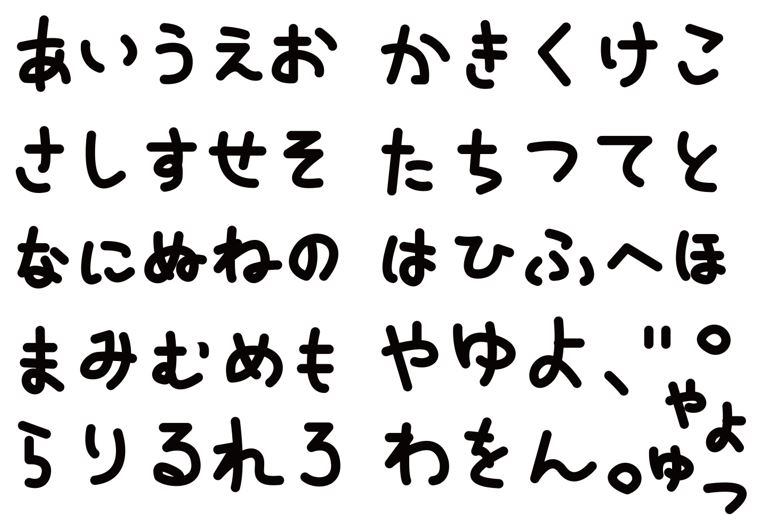
Phông chữ Nhật Bản là gì và sức hút của kiểu chữ phong cách này?
Font chữ Nhật Bản là hệ thống các phông chữ mô phỏng các nét vẽ thư pháp hoặc cấu trúc ký tự đặc trưng của xứ sở hoa anh đào. Đặc trưng của font Nhật Bản là sự kết hợp giữa những đường nét mạnh mẽ, dứt khoát của kiếm đạo và sự mềm mại, uyển chuyển của nghệ thuật trà đạo. Trong ngôn ngữ đồ họa, font chữ kiểu Nhật Bản mang lại cảm giác bền bỉ, tối giản và vô cùng tinh tế, rất phù hợp với các dự án quảng bá văn hóa và dịch vụ ẩm thực Á Đông.
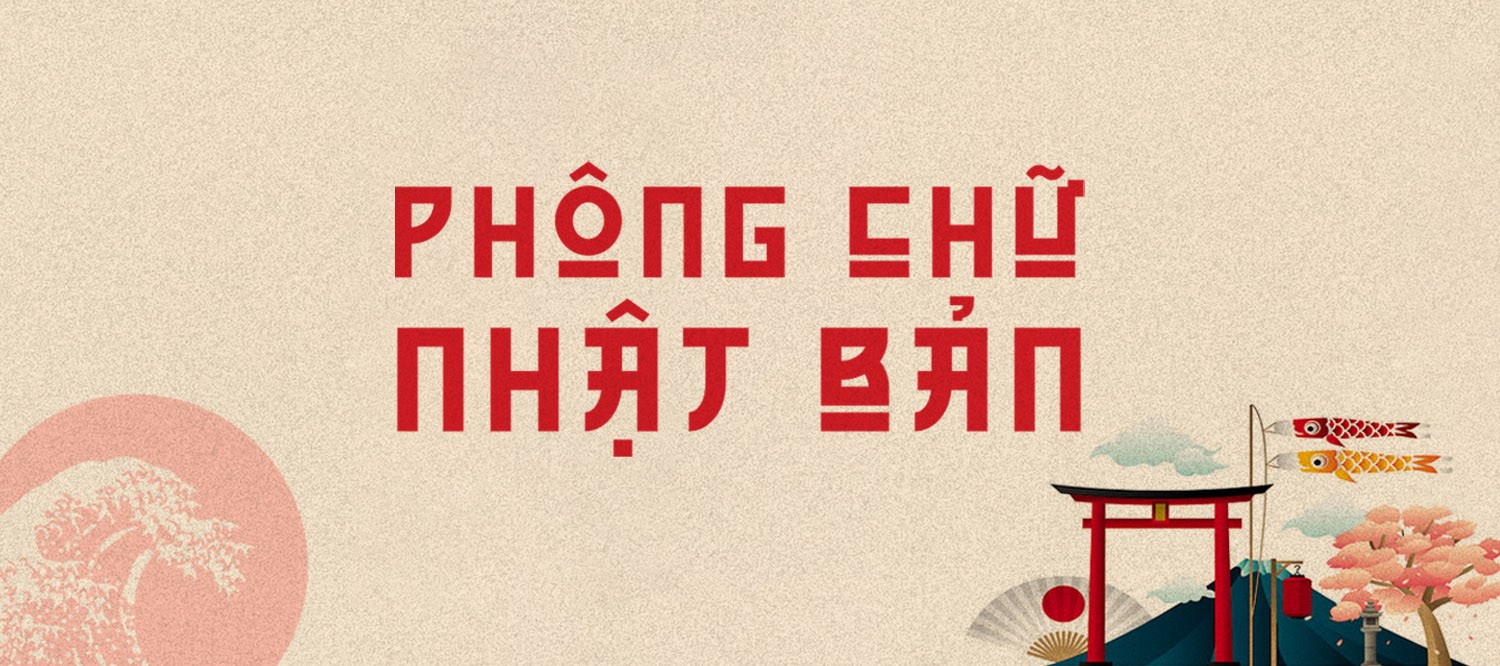
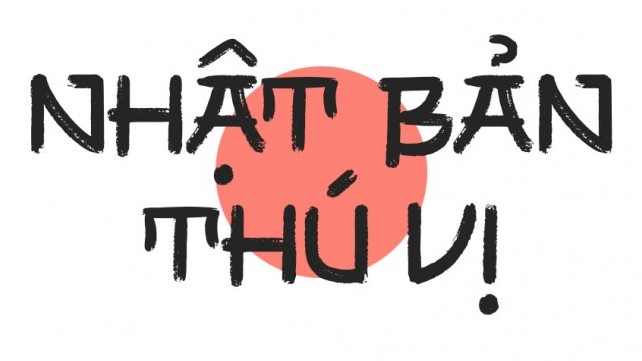
05 Ứng dụng phổ biến của font chữ phong cách Nhật Bản trong sản xuất
Vẻ đẹp mộc mạc và đặc trưng văn hóa của mẫu chữ này nâng tầm giá trị cho nhiều ấn phẩm truyền thông của đơn vị:
- Thiết kế bao bì nông sản và thực phẩm sạch: Sử dụng font chữ Nhật Bản để in trên các dòng túi giấy Kraft đựng trà, gạo hoặc thực phẩm sấy. Những nét chữ tự nhiên tạo cảm giác sản phẩm có nguồn gốc từ thiên nhiên, an toàn và dễ dàng tạo thiện cảm với người tiêu dùng.
- Sản xuất bộ ấn phẩm tri ân khách hàng: Font chữ Nhật Bản đẹp là lựa chọn phù hợp cho các dòng thông điệp vinh danh trên thẻ thành viên hoặc thiệp mời sự kiện. Sự kết hợp giữa nét chữ phá cách và kỹ thuật in hiện đại giúp hiện vật trở nên sang trọng.
- Gia công in UV trên các sản phẩm văn phòng: Logo dùng font Nhật Bản được in trên bình giữ nhiệt kim loại hoặc sổ tay da. Độ sắc sảo của tệp vector giúp các đường cong uốn lượn hiển thị rõ ràng trên các bề mặt sẫm màu, tạo vẻ ngoài bền bỉ.
- Trang trí không gian nhà hàng và Spa: Sử dụng font chữ Nhật Bản Việt hóa cho các câu slogan trên bạt backdrop hoặc chữ nổi mica. Đường nét uyển chuyển của chữ giúp không gian làm việc toát lên sự thư giãn và chuyên nghiệp.
- In nung gốm sứ bộ lưu niệm: Hình ảnh chữ nghệ thuật dùng phông Nhật Bản in nung trên men sứ trắng mang lại vẻ đẹp nhã nhặn, cổ kính cho các bộ ấm chén, là hiện vật trưng bày tinh tế cho các buổi lễ ký kết.
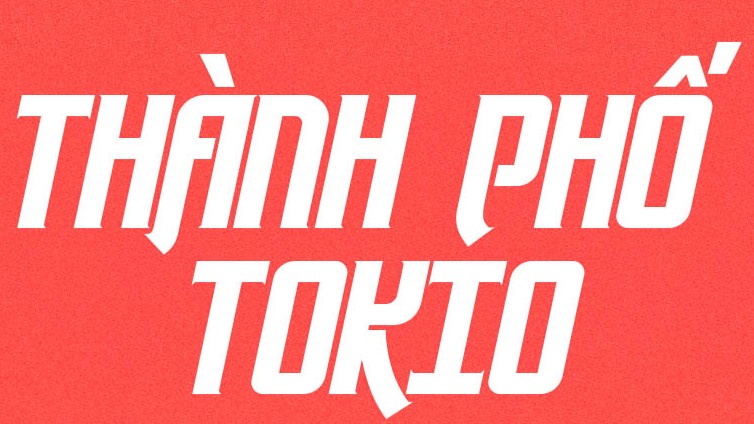
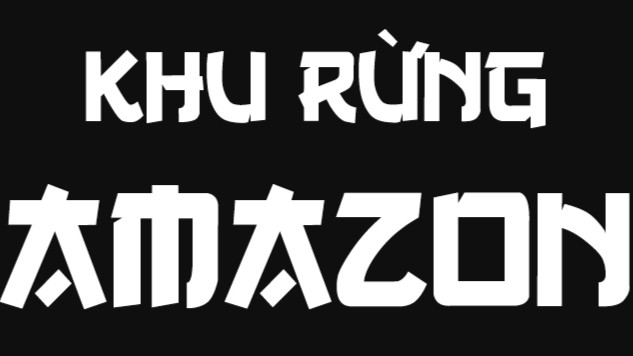
04 Lưu ý kỹ thuật khi sử dụng phông chữ Nhật Bản in ấn
Để hệ thống ký tự font chữ Nhật Bản full hiển thị sống động và bền màu trên các thành phẩm thực tế như túi giấy cao cấp hay hiện vật tri ân đối tác, designer cần chú trọng:
- Kiểm soát độ dày nét theo vật liệu: Font chữ Nhật Bản thường có nhiều nét móc và vòng xoáy nhỏ giả lập vết cọ. Khi in trên túi giấy Kraft có độ thấm mực cao, bạn nên chọn biến thể có nét dày để tránh tình trạng mực loang làm chữ bị dính vào nhau gây mất dáng chữ.
- Tối ưu đường Path cho gia công bế nổi: Bước này quan trọng khi sản xuất nắp hộp cứng dập nổi logo doanh nghiệp. Kỹ thuật viên cần làm mượt từng điểm neo tròn trong file vector giúp khuôn bế thực hiện chính xác, tạo hiệu ứng nổi khối rạng rỡ cho các chi tiết uốn lượn mà không làm rách giấy mỹ thuật.
- Thiết lập hệ màu CMYK cho dải màu rực rỡ: Chữ kiểu Nhật thường đi cùng các tông màu đỏ chu sa hoặc cam đất. Designer cần hiệu chỉnh hệ màu CMYK chuẩn và yêu cầu xưởng in mẫu thử để đảm bảo màu chữ sau in không bị ám xám hay mất sắc độ so với bản vẽ gốc.
- Bảo toàn tính chính xác của dấu thanh: Font Nhật Bản Việt hóa có hệ thống dấu thanh được lồng ghép thủ công. Bạn nên kiểm tra kỹ khoảng cách các lớp màu để đảm bảo mực in không bị chồng lấn quá dày gây hiện tượng gồ ghề bề mặt sau khi gia công cán màng bảo vệ thành phẩm.